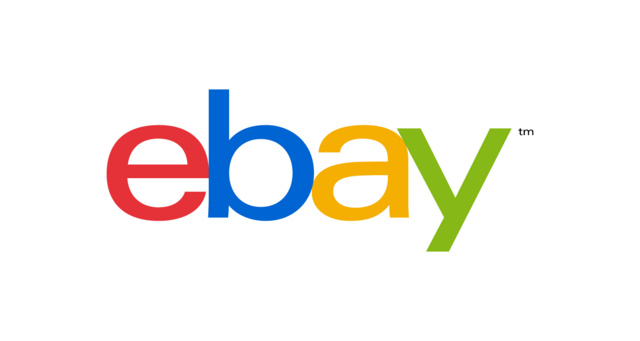
Neues Ebay-Logo
Univers Extended? Cool! Wie auch die Einführungsseite (wow – sogar komplett mit Univers-Webfonts umgesetzt!). :-D Da funktioniert die klare und einfachere Optik zumindest ganz gut, weil sie mit raffinierten Web-Features gepaart wurde. Würde man auf der Portalseite nur das Logo tauschen, könnte das eher wie ein Schritt zurück wirken. Deshalb bin ich auch gespannt, ob und was sie sich dort entsprechend einfallen lassen.
M. E. hinkt das ganze: eine klare, einfache Groteskschrift, die ja an sich ganz aufgeräumt wirkt und dann wird sie so eigenartig zusammengefügt, damit es ein wenig Unverwechselbarkeit bekommt. Da war das alte irgendwie konsistenter.
Aber das Scrollen auf der oben gelinkten Seite finde ich spannend :nicken:
Jessasmarieundjosef … was reitet einen Marketingverantwortlichen, ein derart bekanntes Markenzeichen vom Praktikanten neu hinschubsen zu lassen?
Nichts gegen Univers, aber doch bitte nicht in dieser banalen Art und Weise für ein solches Schwergewicht. Vorher war es ja auch die Univers, aber wenigstens mit mehr Kraft und in einer halbwegs kennfähigen Gestaltung. Die neue ebay-Wortmarke ist langweilig und völlig kraftlos. Die Buchstaben berühren sich merkwürdig – nichts Ganzes, nichts Halbes. Die Wortmarke wirkt für mich wie ein Fehler, da ich den Eindruck habe, hier wäre statt der „echten“ Hausschrift eine Ersatzschrift geladen. Sorry, aber da wurde gepfuscht.
ich mag es. es passt zum zeitgeist. das alte ja war schon etwas in die zeit gekommen und es hatte sich schon etwas 90er jahre staub auf dem logo angesammelt. es passt zu den ganzen reduktionen die man in letzter zeit sieht. sicher ist es nicht der große wurf aber warum sollte man das rad neuerfinden, dank der farbumgebung fühlt man sich sofort an den alten schriftzug erinnert. generell wirkt es auch etwas seriöser und nicht mehr so nach flohmarkt, ebay will sich ja schon seit einiger zeit neu ausrichten. weg vom flohmarktimage und mehr in richtung 'wir-haben-alles-was-sie-benötigen-shop'.
und dazu passt die frische wortmarke ganz gut.
ich hoffe nur die neue seite wird ebenfalls überarbeitet und reduziert, nur das logo austauschen wäre eher ein schritt zurück.
… das alte ja war schon etwas in die zeit gekommen und es hatte sich schon etwas 90er jahre staub auf dem logo angesammelt.…
Das ist unbestritten. Das neue Logo ist aber arg einfallslos, austauschbar und kraftlos. Zudem sieht es aus wie google ohne Serifen.
ich hoffe nur die neue seite wird ebenfalls überarbeitet und reduziert, nur das logo austauschen wäre eher ein schritt zurück.
Das ist unbestritten. Das neue Logo ist aber arg einfallslos, austauschbar und kraftlos. Zudem sieht es aus wie google ohne Serifen.
man könnte auch sagen es stellt sich in die reihe anderer minimaler logos, siehe:
microsoft, windows, apple ...
ich finde nicht das es aussieht wie google ohne serifen, denn da steht ja nicht google sondern ebay ;)
das die farbumgebung von anderen firmen ebenfalls genutzt wird ist natürlich blöd, die frage ist
aber ... wer war hier eher da? ebay, google, msn, windows ...
Offtopic:
… ein derart bekanntes Markenzeichen vom Praktikanten neu hinschubsen zu lassen?
Gibt es einen besonderen Grund, weshalb bei (gefühlt) 99 Prozent aller Logo-Neuvorstellungen genau dieser extrem überhebliche Spruch von irgendjemanden kommt? In genauso vielen Fällen ist er überflüssig wie ein Kropf.
auch gern genommen:
"das mach ich* in 5 minuten."
bei vielem wird die eigentliche kreationsphase vergessen.
sicher ist ein reduziertes in 5 minuten nachgemacht, die betonung
liegt allerdings auf nachgemacht. die idee, bzw. der weg zum fertigen
ergebniss dauert mit sicherheit länger.
* ich kann man auch gleichsetzten mit: meine oma, mein 5 jähriger sohn usw.
Offtopic: Gibt es einen besonderen Grund, weshalb bei (gefühlt) 99 Prozent aller Logo-Neuvorstellungen genau dieser extrem überhebliche Spruch von irgendjemanden kommt? In genauso vielen Fällen ist er überflüssig wie ein Kropf.
Warum ist der Spruch überheblich?
Weiß man denn, ob es der Praktikant war oder degradiert man mit so einer Aussage bewusst den Gestalter zu einem solchen? Was weiß man über das Kommunikationskonzept, welches diese Gestaltungsmaßnahme nach sich zieht und was über Entwurfsvarianten, welche der Kunde nicht wollte?
Aber anstatt auf meinen Äußerungen herumzureiten wäre es doch viel spannender, wenn du selbst Roberts Frage "was haltet ihr davon?" beantwortest.
inwiefern? weil keiner die marke mehr erkennt? …
Weil der Schritt zu radikal ist. Es sind ja nicht die 4 Buchstaben, die du liest, sondern es ist die Gesamtform, die du wahrnimmst. Außenform, Farbintensität, Grauwert, Dicken, etc. Davon ist nichts übrig. Eine verhaltenere Renovierung wäre sicher zuträglicher gewesen.